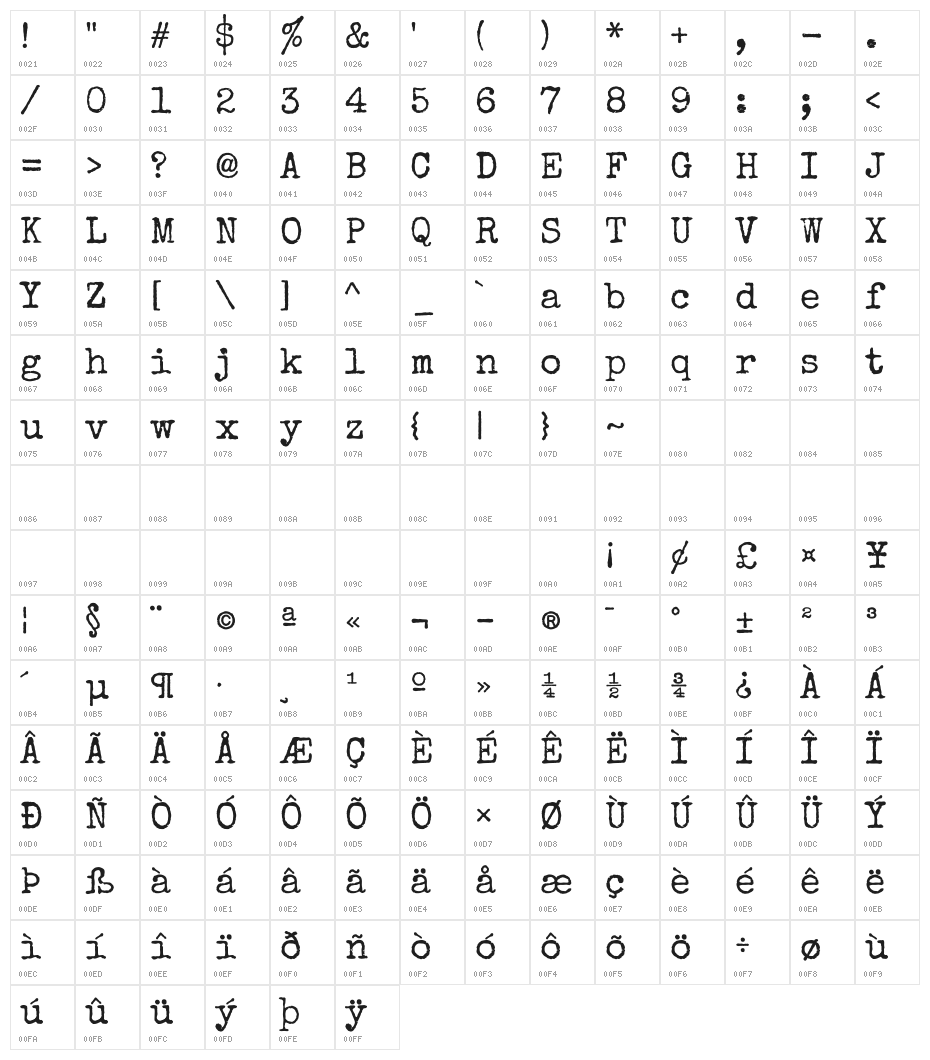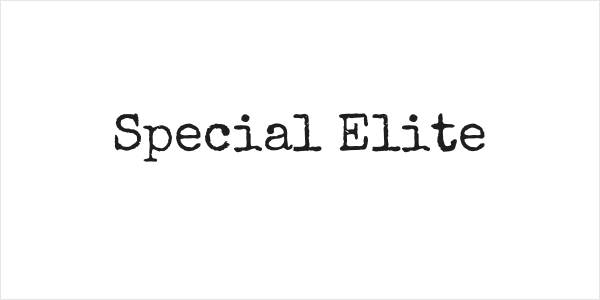
Special Elite Font
✎ Typewriter
Fonts by Astigmatic One Eye Typographic Institute - Brian J. Bonislawsky - astigmatic.com
| 分类 | Typewriter |
| 整体风格 | Vintage |
| 推荐项目 | Ideal for projects that require a retro or vintage feel, such as posters, invitations, branding for artisanal products, or any design that aims to evoke nostalgia. |